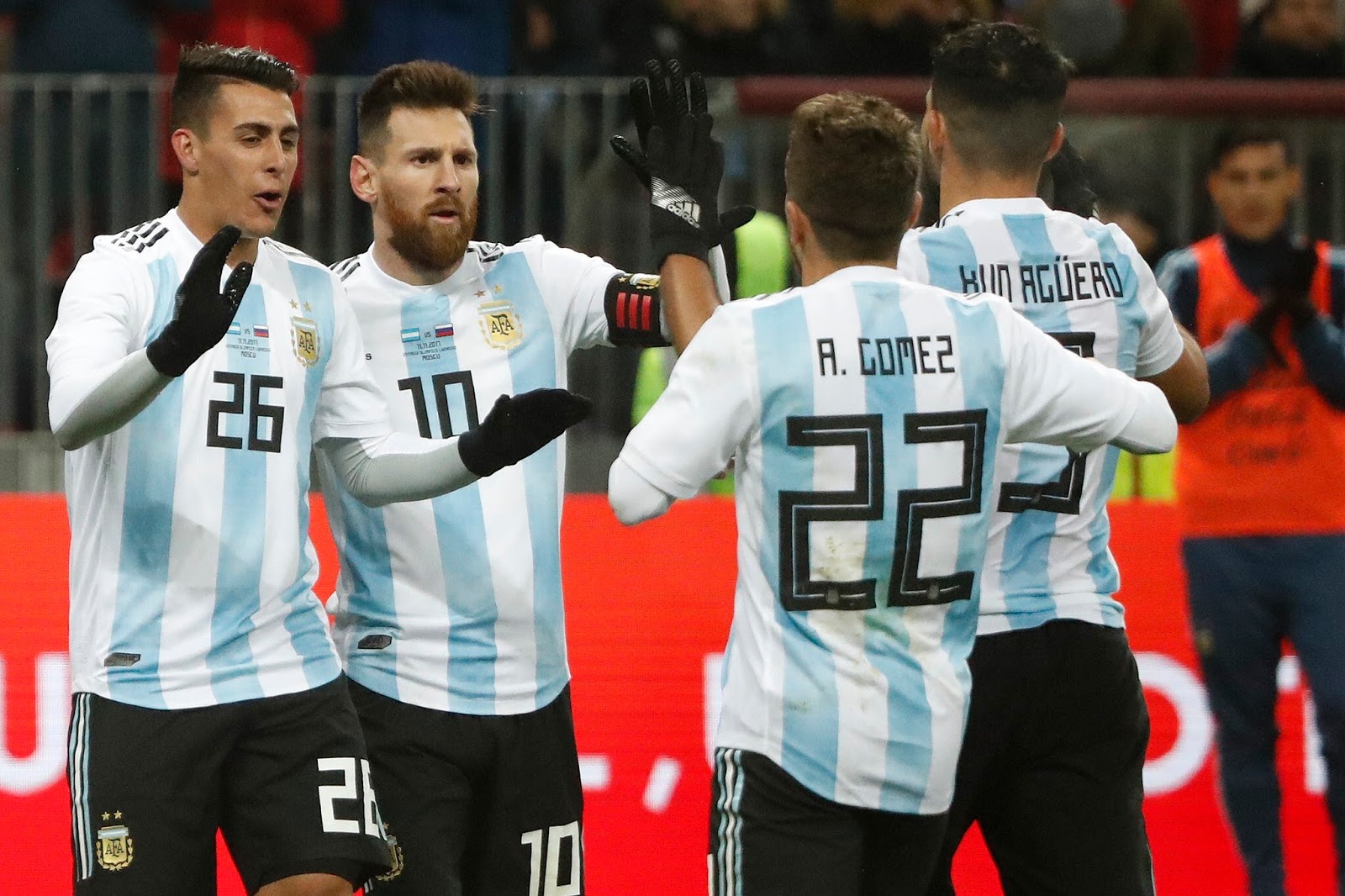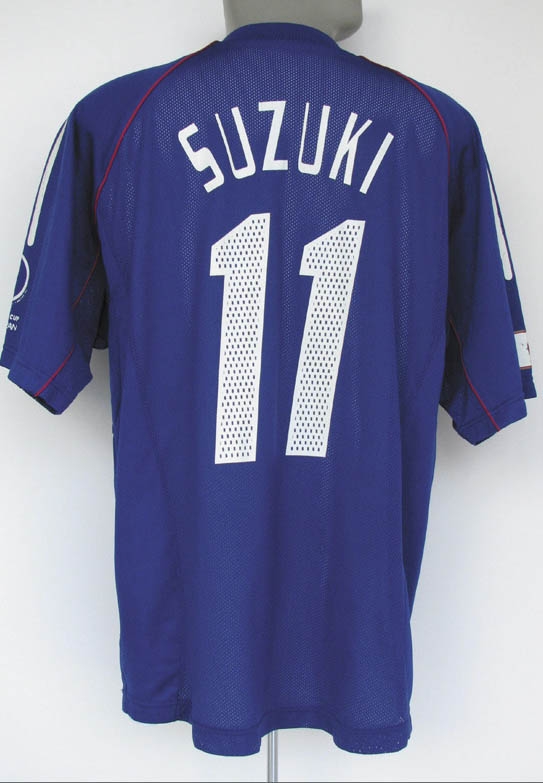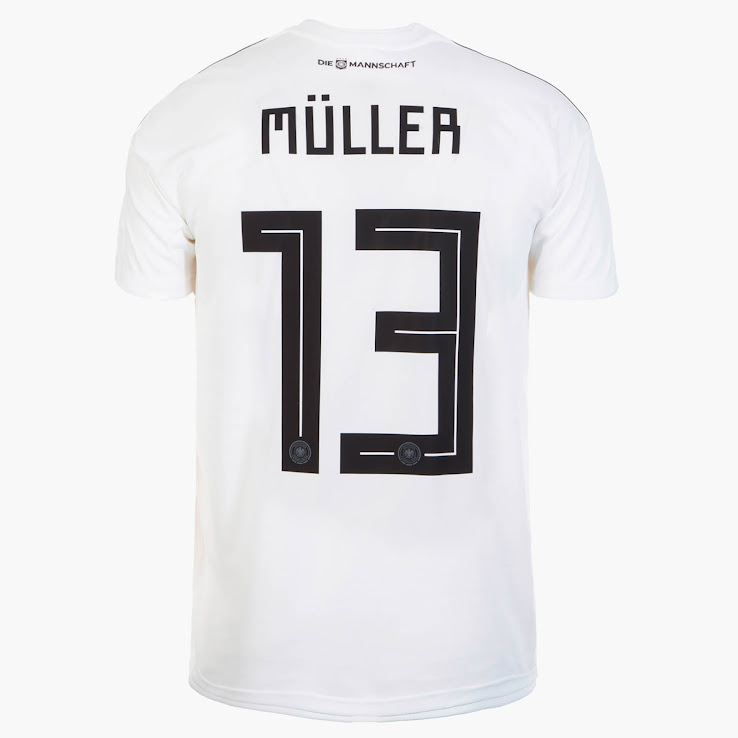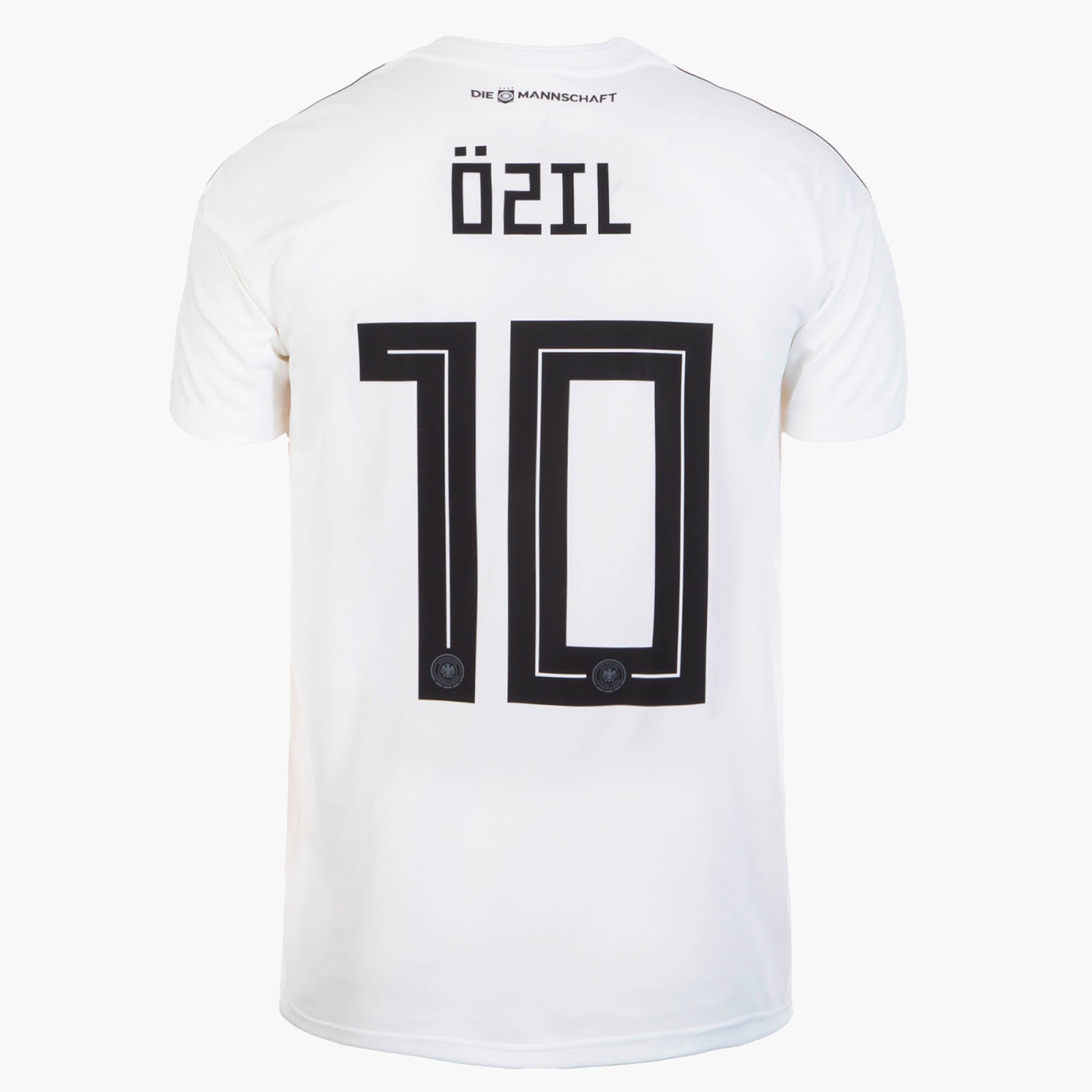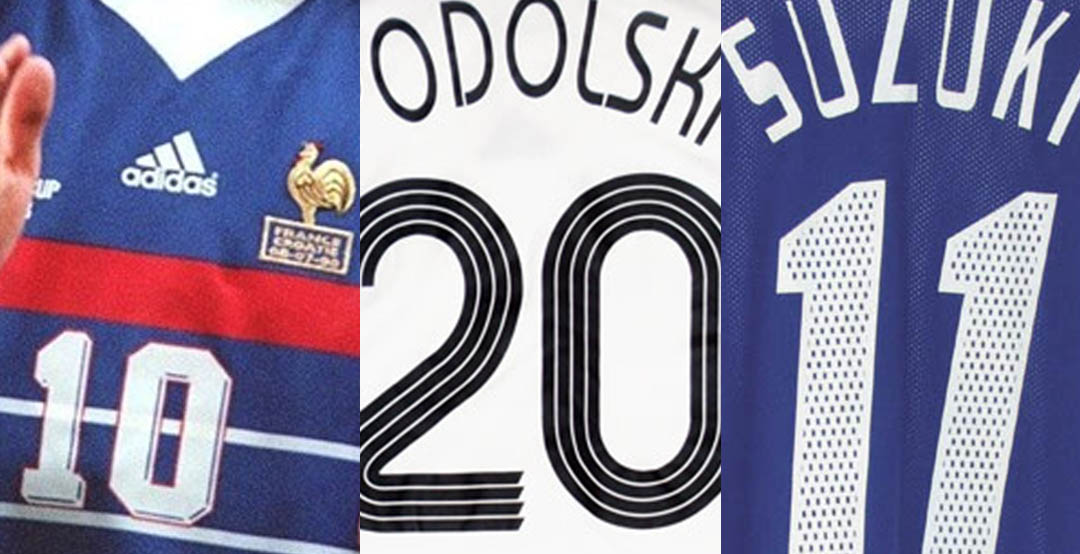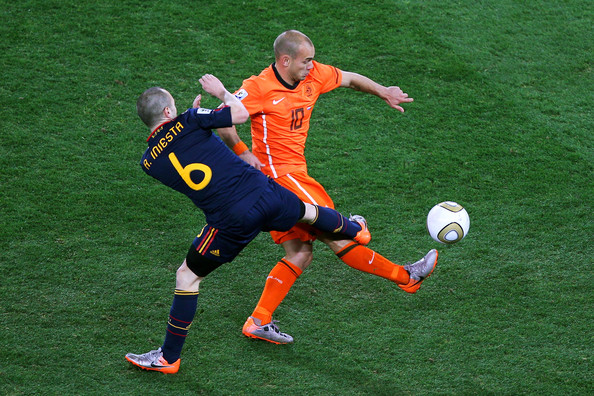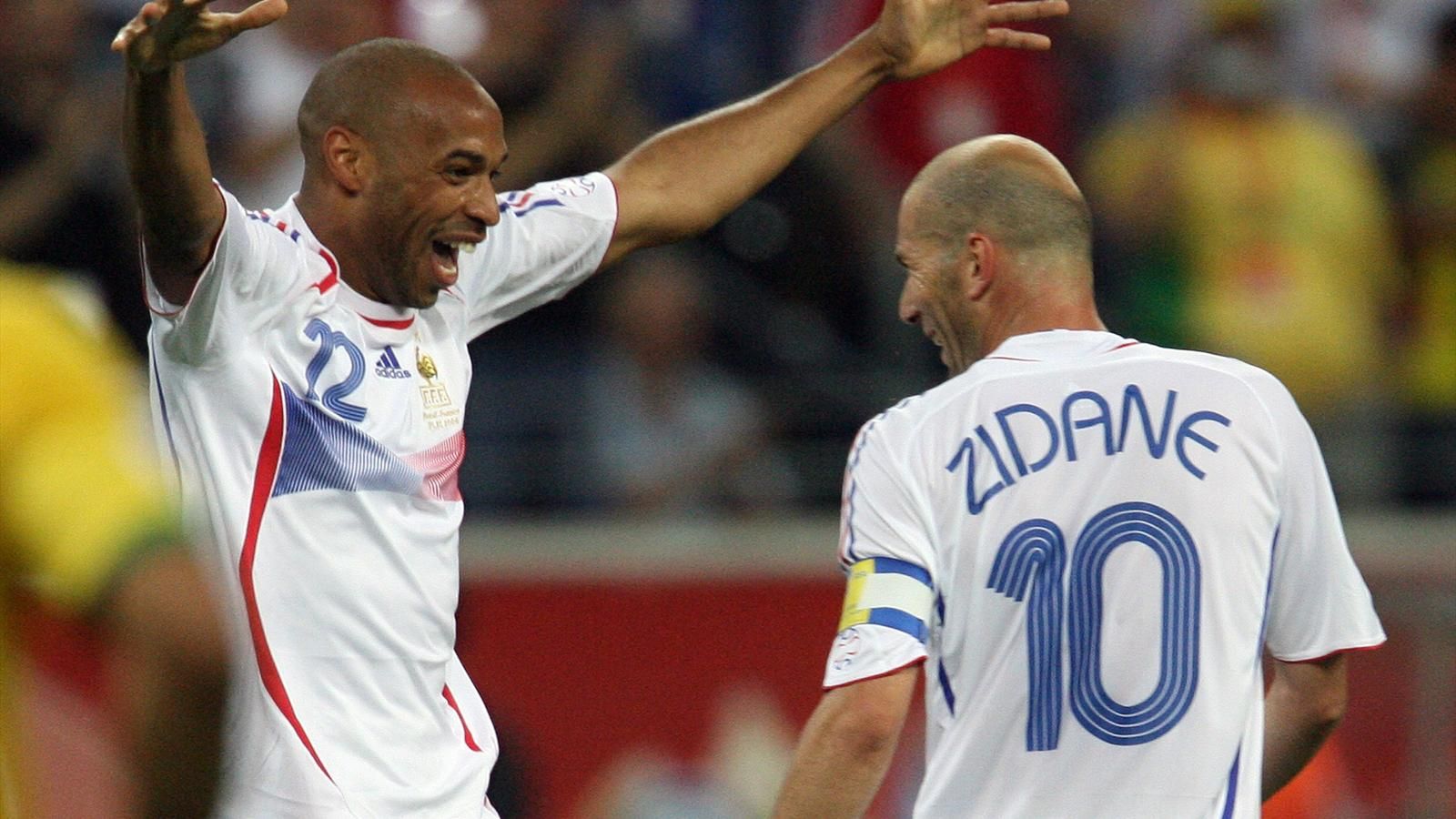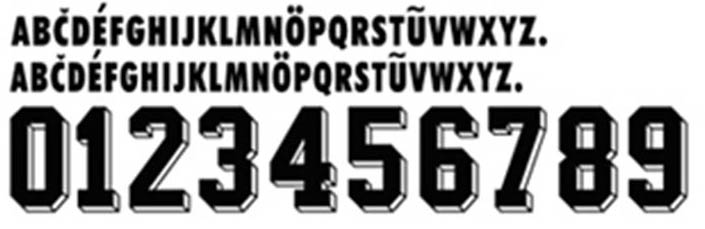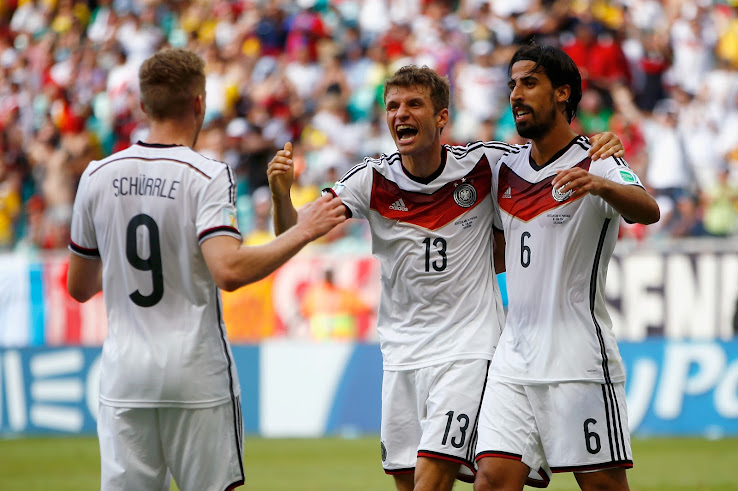
Im Detail | Adidas WM Schriftarten über die Zeit hinweg | 1990-2018
Während Adidas ihre WM 2018 Heimtrikots mit der neuen WM-Schriftart veröffentlicht hat, werfen wir einen Blick auf alle Adidas WM-Schriftarten zwischen 1990 und 2018. Vielen Dank an Paladar Negro, Switch Image Project & einige andere großartige Webseiten für Infos und Bilder.
Adidas WM 1990 Schriftart
Adidas WM 1990 Schriftart zeichnet sich durch einen einfachen 3D-Look aus.
Adidas WM 1994 Schriftart
Argentiniens und Spaniens WM 1994 Schriftart waren anders als die Schriftart, die andere Adidas-Länder verwendeten.
Die Adidas WM 1994 Schriftart in den USA ist die gleiche wie die für die WM 1990. Die US-Nationalmannschaft hat jedoch eine einzigartige & moderne Schriftart von den Drei Streifen für ihre Heim-WM erhalten.
Adidas WM 1998 Schriftart
Die Adidas WM 1998 Schriftart ist ebenfalls unverändert gegenüber zuvor. Deutschland und Spanien haben jedoch unterschiedliche, einzigartige Schriftarten für das Turnier erhalten.
Adidas WM 2002 Schriftart
Die Adidas WM 2002 Schriftart ist mit einem modernen Design vollkommen anders zu den vorherigen Schriftarten, die Adidas-Teams bei der WM verwendet haben. Die Sprung nach vorne gegenüber der klassischen WM 1998 Schriftart ist bemerkenswert.
Adidas WM 2006 Schriftart
Die Adidas WM 2006 Schriftart, die bis heute berühmteste Adidas WM-Schriftart, ist ein Designklassiker. Der Stil wurde von der Schriftart inspiriert, die bei der WM 1974 verwendet wurde.
Adidas WM 2010 Schriftart
Die Adidas Unity WM 2010 Schriftart, die einen deutlich weniger bemerkenswerten Look hat, wurde vom gesamten WM 2010 Motiv inspiriert.
Adidas WM 2014 Schriftart
Die WM 2014 Schriftart weist ein modernes, dennoch einzigartiges Design auf.
Adidas WM 2018 Schriftart
Für die WM 2018 haben sich die Drei Streifen dafür entschieden, zum ersten Mal das jeweilige Wappen jedes Verbands am unteren Ende hinzuzufügen, um den Nummern ein maßgeschneiderteres Gefühl zu verleihen. Finde alles, was du über die Adidas WM 2018 Schriftart wissen musst, heraus.